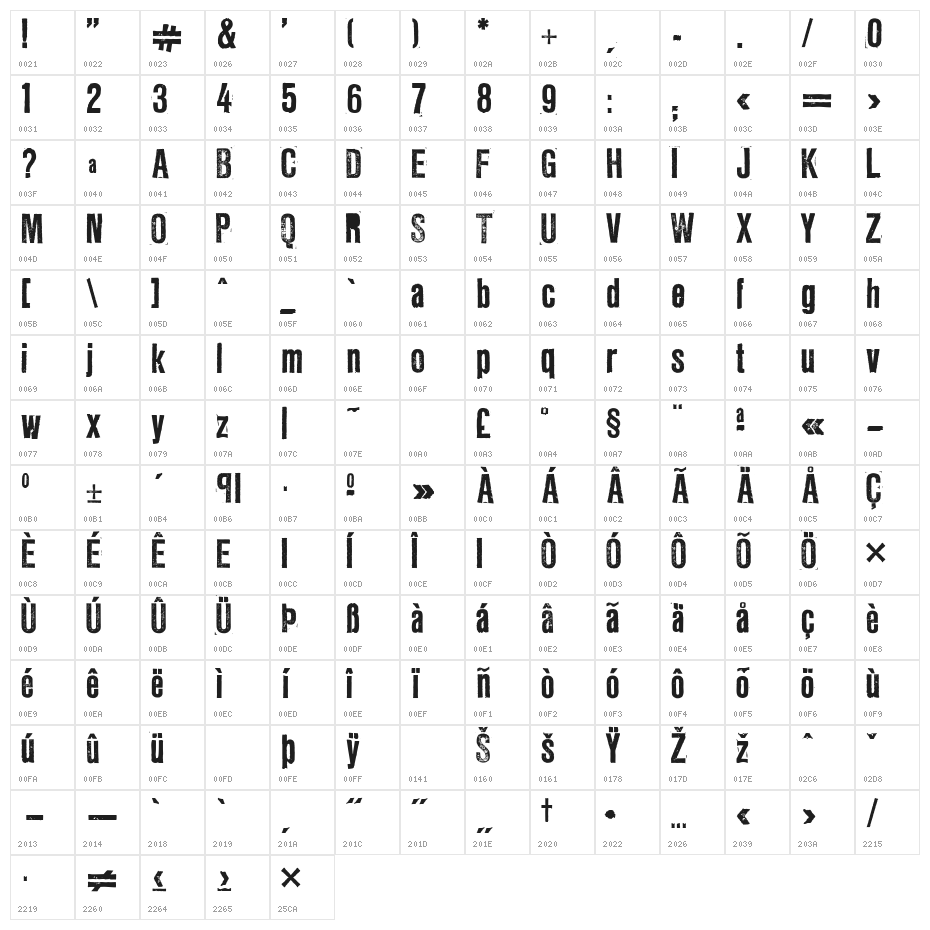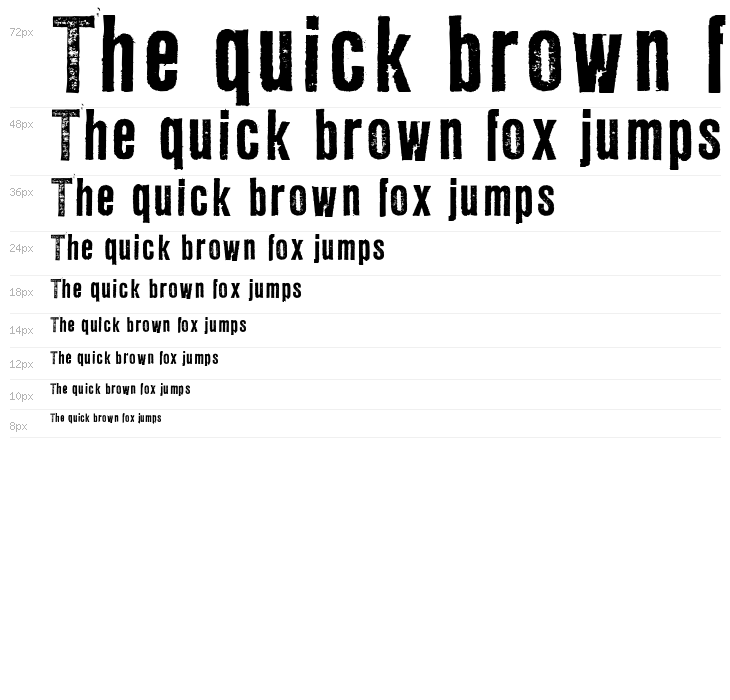
L Regular Font
✎ Messy
| Progetti proposti | Ideal for posters, album covers, branding for rustic or industrial-themed businesses, and any design needing a bold, gritty aesthetic. |